Das Ende der PostScript-Fonts ist da. Sind Sie vorbereitet?
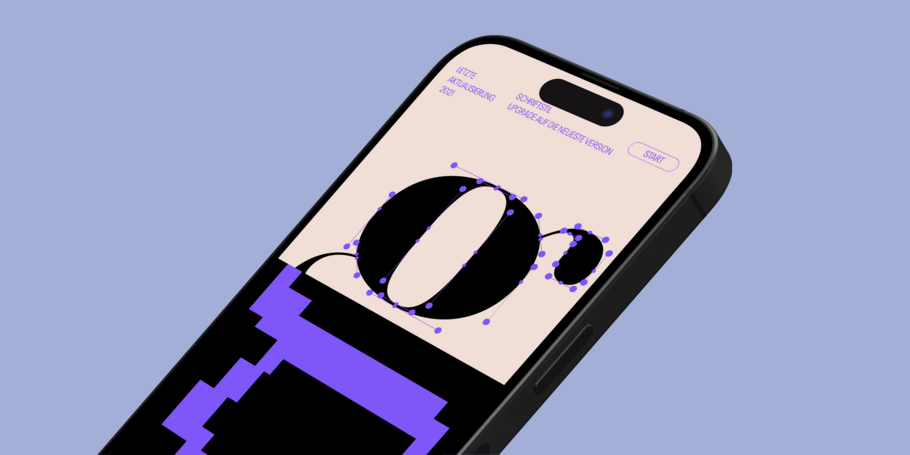
Adobe hat im Januar 2023 die Unterstützung für das PostScript-Font-Format eingestellt, auch bekannt als PS1-, T1- und Adobe-Type-1-Schriften. Für die Praxis heißt das: Sie können keine neuen Inhalte mehr mit den Type-1-Fonts von Adobe erstellen. Lesen Sie hier, ob und wie Sie Ihre Schriftbibliothek aktualisieren müssen oder können.
Von Photoshop werden Type-1-Fonts bereits nicht mehr unterstützt. Im Laufe des Jahres werden weitere Programme der Adobe Creative Cloud folgen. Diese Entwicklung hat auch Einfluss auf andere Plattformen und Dokument-Formate. Laut einem Support-Dokument von Apple, das zur Veröffentlichung von macOS 13 Ventura erschien, unterstützt die Vorschau-App keine Dateien im Format PostScript (.ps) und Encapsulated PostScript (.eps) mehr.
Verwenden Sie noch Type-1-Schriften? Lesen Sie weiter, um zu erfahren, was Sie über dieses Schriftformat wissen müssen.
Was sind Type-1-Schriften?
Die 1984 entwickelten vektorbasierten Schriften wurden für die Verwendung mit der Seitenbeschreibungssprache PostScript von Adobe konzipiert und läuteten das Desktop Publishing (DTP) ein. Type-1-Schriften ließen sich schnell und sicher drucken. Dank der damals revolutionären Hinting-Technologie garantierten sie bei den niedrigen auflösenden Laserdruckern (300 dpi) ein klares Schriftbild. Doch Adobes Patentpolitik löste bald einen Wettbewerb unter den Computerherstellern aus und führte 1991 zur Einführung des TrueType-Formats durch Apple. Ein Jahr später wurde TrueType das Font-Format von Microsofts Windows 3. 1996 einigte sich die Branche auf das universelle Font-Format OpenType, das wesentliche Begrenzungen von TrueType und Type-1 überwand. OpenType-Schriften gibt es in den beiden Ausprägungen TrueType-flavoured (.ttf) und PostScript-flavoured (.otf), die beide plattformübergreifend funktionieren und heute die bevorzugten Font-Formate sind.
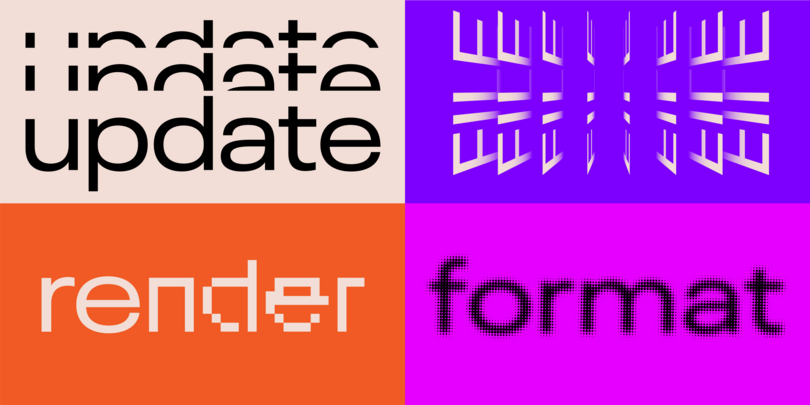
Was passiert, wenn die Unterstützung für Type-1 eingestellt wird?
Sie fragen sich vielleicht: „Was ist schon dabei? PostScript-Schriften gibt es doch schon seit Jahrzehnten und sie werden von vielen Menschen in aller Welt für digitale und gedruckte Dokumente verwendet.“ Das stimmt nicht mehr ganz. Obwohl sie früher weit verbreitet waren, sind PostScript-Fonts heute nicht mehr zuverlässig. PostScript-Fonts funktionieren nicht auf neueren Betriebssystemen und sind mit neueren Browsern wie Microsoft Edge™ oder Mozilla Firefox® Quantum inkompatibel, das heißt, wenn Ihre Website diese Art von Schriften verwendet, werden Ihre Texte in diesen Browsern nicht richtig angezeigt.
Aktualisierte Versionen von Adobe-Anwendungen erkennen Type-1-Schriften nicht mehr, selbst wenn sie sich auf Ihrem Rechner noch installieren lassen. Sie werden im Schriftmenü der Adobe-Programme nicht angezeigt, sodass Sie mit Ihren Type-1-Fonts keine neuen Inhalte erstellen können. Beim Öffnen älterer Dokumente, die mit Type-1-Fonts erstellt wurden, erscheint die Fehlermeldung „fehlende Schrift“. Ältere Versionen von Creative-Cloud-Anwendungen unterstützen die Type-1-Fonts vielleicht noch, aber Vorsicht: Viele Betriebssysteme folgen dem Beispiel von Adobe und stellen ebenfalls die Unterstützung für Type-1-Schriften ein. Wenn dies geschieht, werden die alten Fonts in den Adobe-Programmen nicht mehr geladen bzw. angezeigt.
Type-1-Schriften, die in Dateien im Portable Document Format (PDF) oder Encapsulated Postscript (EPS) eingebettet sind, werden auch nach der Einstellung der Unterstützung noch angezeigt, aber Sie können keine Änderungen an den Texten vornehmen. Nicht in diesen Dateiformaten eingebettete Schriften werden durch Standardschriften ersetzt.
So erkennen Sie PostScript-Type-1-Schriften
Öffnen Sie die Spotlight-Suche, indem Sie Befehlstaste + Leertaste oder die Funktionstaste mit der Lupe drücken, und geben Sie Schriftsammlung in das Suchfeld ein; öffnen Sie das gefundene Programm. Bis MacOS 12 Monterey: Klicken Sie auf die Lupe, wählen Sie Art und geben Sie Type 1 in das Suchfeld ein. Das generiert eine Liste aller PostScript-Type-1-Fonts, die aktuell auf Ihrem Rechner aktiviert sind. Ab MacOS 13 Ventura: Geben Sie Postscript in das Suchfeld ein, um die aktiven Type-1-Fonts zu finden; wählen Sie die tabellarische Ansicht für den besten Überblick.
Anleitung für PC-Benutzer
PC-Benutzer öffnen das Fonts-Kontrollfenster, indem sie mit der rechten Maustaste auf das Startmenü klicken, Ausführen wählen, c:\windows\fonts eingeben und die Enter-Taste drücken. Oben im Fonts-Fenster sollte sich eine Menüleiste befinden. Ist dies nicht der Fall, klicken Sie auf Organisieren und wählen Sie Layout → Menüleiste. Wählen Sie Ansicht → Details und dann Ansicht → Details auswählen. Klicken Sie im Details-auswählen-Fenster auf das Feld Font und klicken Sie auf den Text, um ihn zu markieren. Klicken Sie auf die Schaltfläche Nach oben, bis Font-Format direkt unter Name im Fenster Details auswählen angezeigt wird. Klicken Sie dann auf OK. Nun sollten Sie eine Liste mit allen von Ihren installierten Fonts sehen, die sowohl den Namen als auch das Font-Format enthält. Wenn Sie in der Spaltenüberschrift auf Font-Format klicken, werden alle Schriften nach Typ sortiert; blättern Sie durch die Liste, um alle Type-1-Schriften auf einen Blick zu sehen.
Wenn Sie Type-1-Fonts entdecken, sollten Sie ein Muster jeder dieser Schriften ausdrucken, um später schnell und zuverlässig eine Ersatzschrift zu finden. Fahren Sie dann mit dem nächsten Schritt fort.
Finden Sie heraus, ob und wo noch Type-1-Fonts verwendet werden
Das kann ein mühsamer Selbstversuch werden, vor allem, wenn Sie eine große Schriftbibliothek und langlebige Projekte verwalten, die in unregelmäßigen Abständen aktualisiert werden, z. B. korrigierte Nachdrucke. Programme der Adobe Creative Cloud 2022 schlagen Alarm, wenn sie Type-1-Fonts in einem Dokument entdecken und markieren diese.
Am einfachsten lässt sich dies mit einer integrierten Font-Management-Plattform erreichen. Die hinterlegte Wunschlos-glücklich-Lizenz deckt alle Font-Aktualisierungen mit einem einzigen Vertrag ab, sodass die Notwendigkeit entfällt, einzelne Fonts von verschiedenen Herstellern zu lizenzieren. Funktionen wie die Ein-Klick-Synchronisierung senden Schriften an alle, die sie benötigen, und ermöglichen so nahtlose Aktualisierungen an den Arbeitsplätzen. Dies erübrigt einen langwierigen, mühsamen Austausch von Font-Dateien und es bedeutet auch, dass Sie sich nie wieder Sorgen machen müssen: Wenn wieder mal eine Schrift oder ein Format veraltet ist, sorgt Ihre Font-Plattform automatisch dafür, sie zu ersetzen, bevor Ihr Workflow gestört wird.